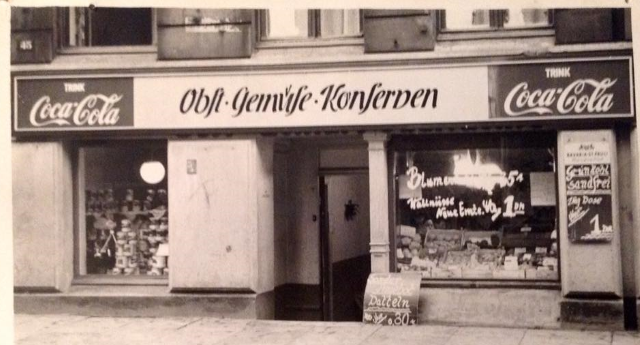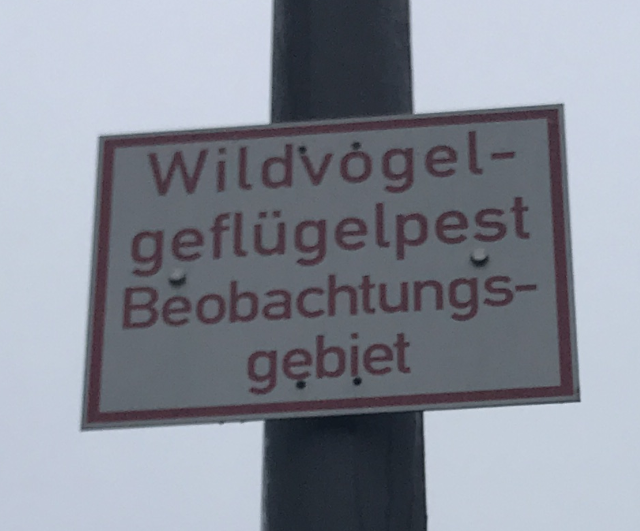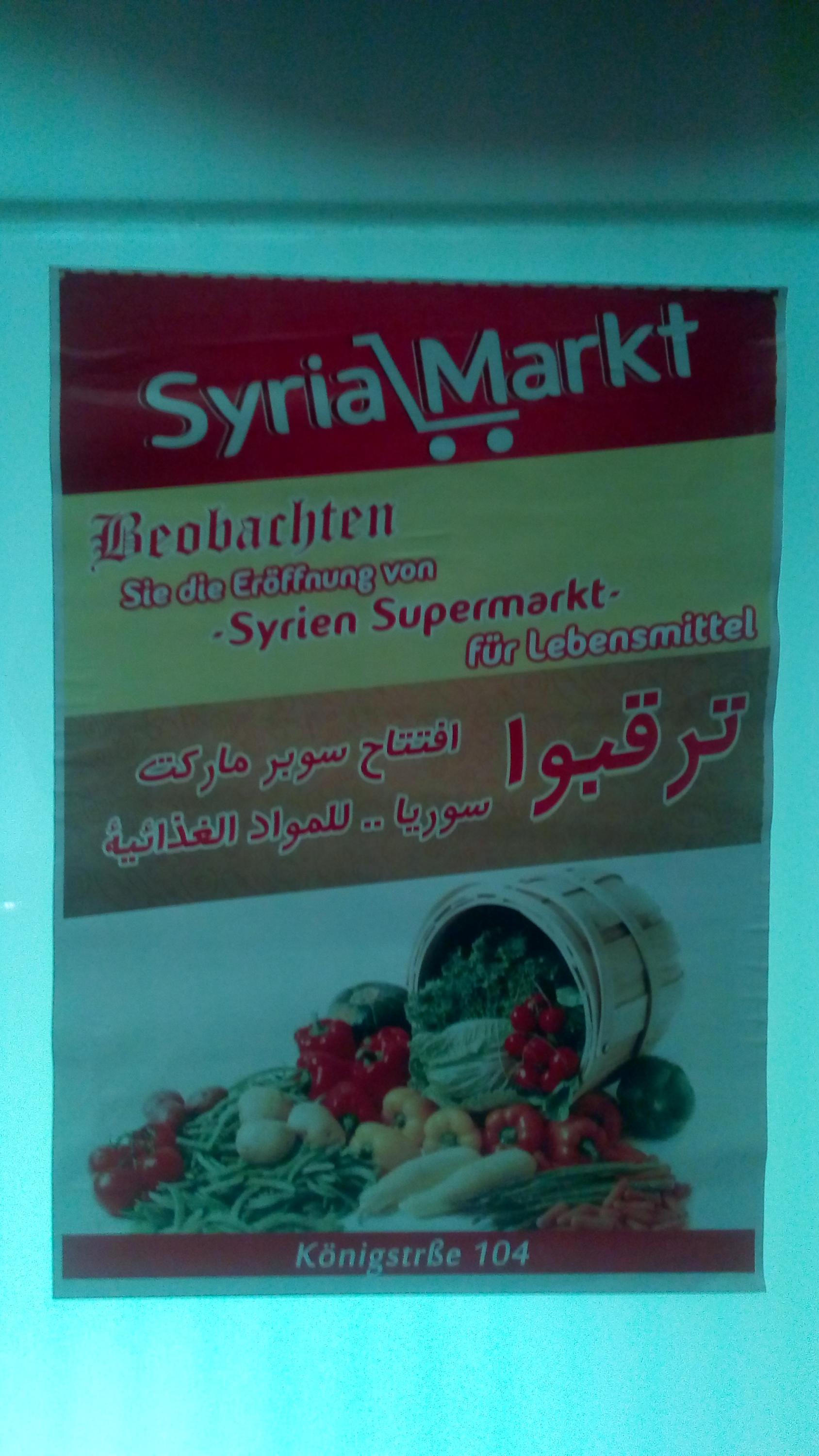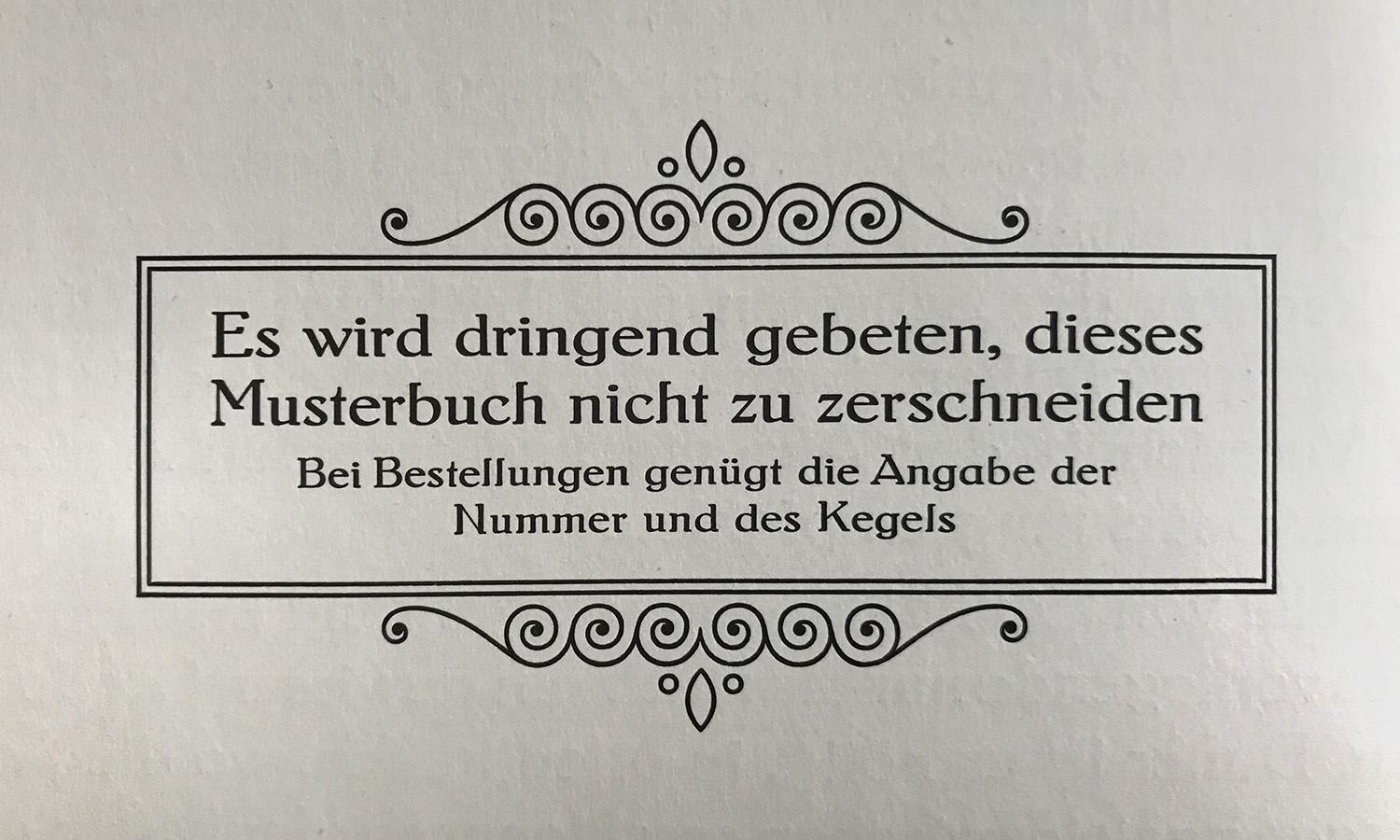
Die einzelnen Lettern anklicken! Mein Favorit ist das P ...
Da müsste es aber beim linken Stick weiter nach unten über das D hinaus zum ь gehen :-)
Im weiteren Sinne typographiebezogen:
Das International Music Score Library Project sammelt bzw. verlinkt gemeinfreie Musik, vertont und/oder die dazugehörigen Noten. Es sind ein paar hübsche Titelblätter zu finden :) Es sind (aufgrund unterschiedlicher Fristen und Regelungen in verschiedenen Ländern, ab wann Kunstwerke gemeinfrei werden), soweit ich das überblicke, um die 54000 Aufnahmen und 455000 Noten vorrätig, ggf. braucht man für das eine oder andere Werk eine nichtdeutsche IP via Proxy oder VPN (auch hilfreich bei anderen Anbietern (zumindest hier und dort) gemeinfreier Werke wie gutenberg.org).
Wenn das zu "illegal" ist, kann der Betrag gerne gelöscht werden, jedoch sehe ich hier den Anspruch, Bewahrung und Zugänglichkeit von Kultur, vorrangig gegenüber der Contentmafia (ein Begriff, den ich in Anbetracht der Raubzüge, die windige Anbieter mit von Google gescannten Büchern via Amazons Print on Demand (bekommt eine ISBN und ist wundersam nicht mehr vergriffen/gemeinfrei und damit abmahnbar) machen/gemacht haben, für gerechtfertigt halte.
Hübsche Schrift, nach Registrierung unter Creative Commons BY-ND 4.0 frei downloadbar. Leider ohne deutsche Umlaute und Sonderzeichen. Aber vielleicht kommen die ja noch irgendwann 🙂
Thanks for your nice comment. FYI all Reforma fonts include the German umlauts as well as minuscule eszet — Only the cap eszet was not included but we hope to extend the Reforma sets in the future, just as any PampaType font set (SuperLatin).
Gibt es eigentlich so etwas wie typografische Forensik? Ein solcher Experte sollte ja z.B. feststellen können, ob ein Dokument mit einer Bleisatz-Times oder einer sehr viel jüngeren Computer-Times erstellt wurde.
Schwieriger wird es, wenn Dokumente in älteren Schriftarten vorliegen. Gute Beispiele sind Arial und Times New Roman: Beide Schriften sind schon sehr alt und stammen aus den Jahren 1982, respektive 1932.
ZEIT online berichtet heute über ein Gebäude des Architekten Oscar Niemeyer namens „Edifício Copan“, dessen Form die Tilde im Wort „São Paulo“ nachempfindet. Schön, oder?
Das habe ich beim Spazieren im neuen Viertel gefunden und muss sagen, ich hätte das ja gnadenlos durchgekoppelt :)
Und das ist mir bei Facebook in die Timeline gespült worden (darf ich hier posten, das Photo stammt aus den Fünzigern und ist in der Seilerstraße aufgenommen worden). Ich finde die Ladenbeschriftung voll spannend, die Glyphen für sich sind irgendwie besoffen tanzend, aber in Gänze wieder harmonisch.
die Glyphen für sich sind irgendwie besoffen tanzend
Wo es sich doch bei Coca-Cola gar nicht um alkoholische Getränke handelt. :party:;-)
Im Dezember in Lübeck in der Nähe des Bahnhofs gefunden. Hatte da bloß ein Smartphone mit sehr schlechter Kamera dabei, also miese Bildqualität, es dunkelte auch schon, und das Plakat hing an einer blau hinterleuchteten Wand. Denkbar schlechte Bedingungen, aber man kann es erkennen 😉